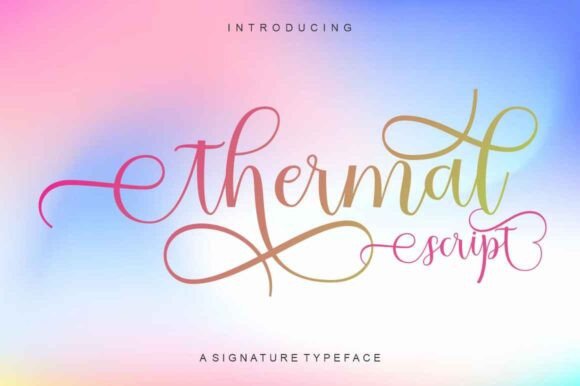
Thermal Script
Encontrar los elementos de diseño adecuados puede ser un desafío, pero Thermal Script ofrece una colección excepcional que eleva tu trabajo al instante.
Ya sea que estés creando productos POD (impresión bajo demanda), invitaciones de boda o gráficos para redes sociales, Thermal Script es una opción ideal.